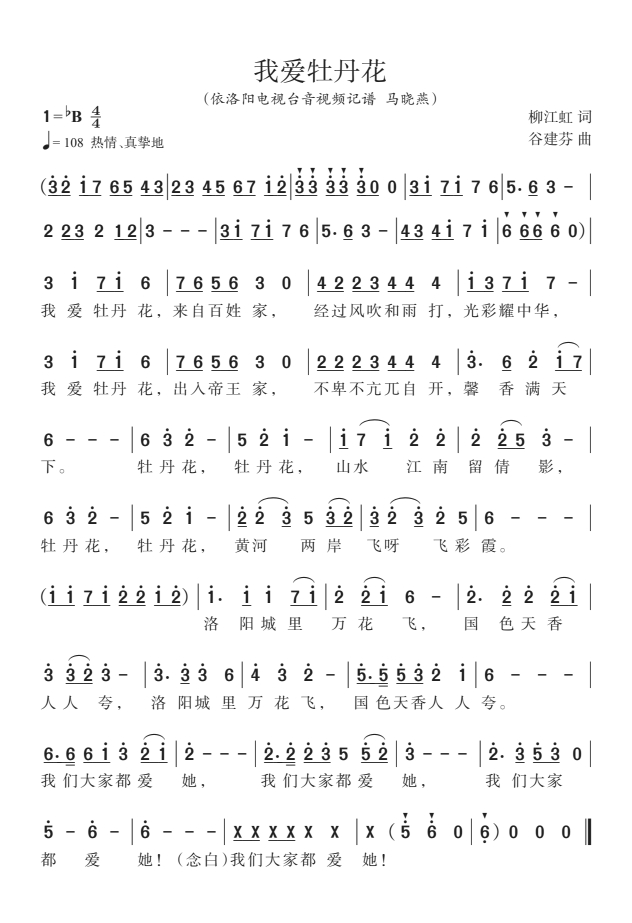
能设置字体的地方就可以录入简谱。怒独僧简谱字体将各种常用字符输出为简谱符号,不借助输入法,直接使用键盘就可以录入简谱。
排版样张《快乐的节日》
排版样张《我爱牡丹花》(A5) (B5) (图片)
当歌词字号小于乐谱字号时,对位会比较麻烦,通过下边的方法可以做到快速精准的对位。
① 将默认制表位设置为乐谱字号的一半,比如乐谱字号12磅,就将默认制表位设置为6磅(磅字要写在输入框中,确定后word会自动转换为毫米)。
② 将乐谱行的缩进设置为(歌词字号 - (乐谱字号/2))/2,比如乐谱字号12磅,歌词字号10磅,则乐谱缩进设置为(10-(12/2))/2 = 2磅。
③ 乐谱中,确保不出现4分空,或者要成对出现。确保带歌词的音符后跟有半宽空格。
④ 歌词中,相邻的两个字之间要用tab键,而不是用空格,距离远时就多用几次tab键。
示例
CorelDraw高版本存在一个默认的字符间距,该选项在段落属性中,找到这个选项将其从20%改为0%,否则减时线、高低音点等无法输出到字符的正上方或正下方。
飞翔的默认字心字身比是98%,会导致连线出现缝隙或者使大部件(如连音线)发生偏移。须在文件菜单→工作环境设置→字心字身比设置中将 jpfont-nds 字体设置为100%。
排版样张: